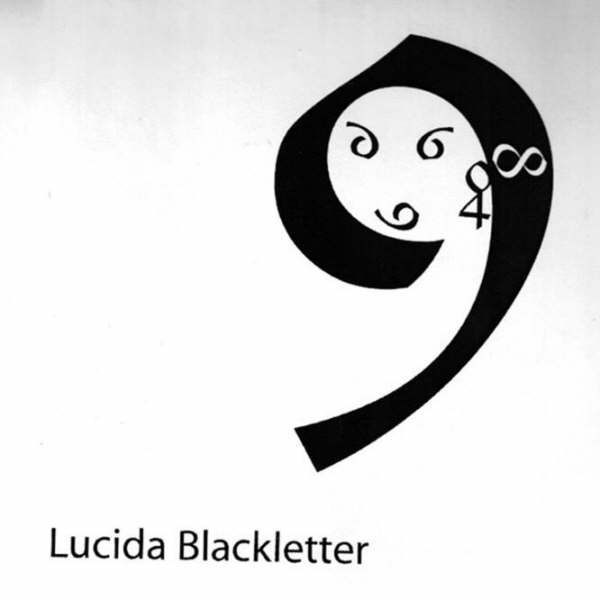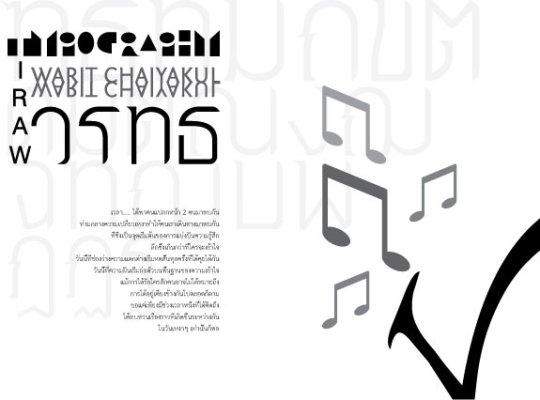
Trial & Error Gallery
เพราะว่าความคิดผมมันไปเร็วกว่ามือนัก
ห้องทดลองผิดทดลองถูก  :09:
อันนี้งานสมัยเรียนปีสองครับ วิชา Typography I  ( edit เอาเบอร์มือถือออก  :39: )
เป็นงานที่ให้เราออกแบบโปสเตอร์นิทรรศการศิลปะ โดยให้เลียนแบบสไตล์งานของ Typographer
ตามที่จับฉลากได้ ( ผมได้ Neville Brody ครับ เลยชอบงาน Typo นับแต่นั้นมา )
อันนี้ Typography II ครับ เผื่อใครเห็นแล้วจะเกิด inspiration  :52:
ของจริงมี 12 ภาพครับ แต่เหลืออยู่ 4  :05:
งานข้างล่างนี้เป็นโปรเจคชื่อ Type Face  ( ไม่ใช่ Typeface นะครับ )
เป็นการให้สร้างหน้าคนจากตัวหนังสือ โดยมีข้อแม้ว่าตัวหนังสือนั้นๆห้ามถูกบีบ ดึง ยืด ให้ผิด scale
นี่คือข้อกำหนดในการใช้ฟอนต์ ( ผมเริ่มลืมๆแล้วว่ามีอะไรบ้าง จะเอาเท่าที่นึกออกนะครับ )
1. ภาษาไทยอย่างเดียว
2. เลขไทยอย่างเดียว
3. ภาษาอังกฤษอย่างเดียว
4. เลขอารบิกอย่างเดียว
5. ภาษาไทย + ภาษาอังกฤษ
6. เลขไทย + เลขอารบิก
ทั้งหมดอย่างละ 2 ภาพครับ
คอนเสปต์ผมคือ หญิงสาวผู้มีความสุข  :33:
:25: ช่วยขยายความวิชาที่เรียนด้วยสิครับ จะได้รู้ว่าทำอะไร
นี่น่าสนุกมากเลยนะเนี่ย ทำไมตูไม่ได้เรียนมั่งนะ :05:
แถมอีกงานสำหรับวันนี้  เป็นงานตอนปีสามนี่เอง เป็นงานพรีเซ้นต์ตัวเอง
( ตอนนั้นรู้ตัวว่าไทโป แน่แล้ว เลยใส่ไม่ยั้งเลย  :01: )
ไม่ค่อยรู้จักงา่นแนวนี้เท่าไหร่ แต่ดูแล้วมันเจ๋งมากเลยนะคะ  :12:
คงต้องใช้จินตนาการเยอะมากๆ เลย
ชอบที่เอาตัวอักษรมาทำเป็นรูปผู้หญิงมาก  :25: :25: